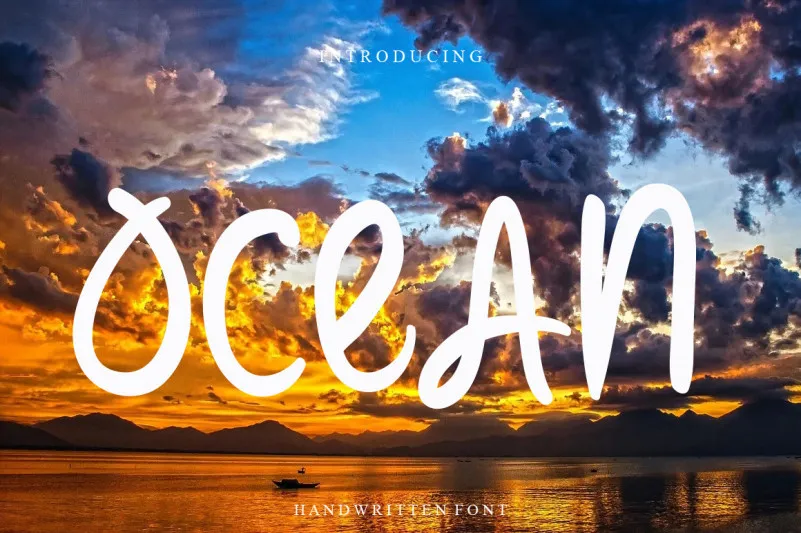
A Ocean Font é uma elegante escolha para quem busca criar designs modernos e descontraídos que transmitem alegria e frescor. Essa fonte script traz a sensação de um convite festivo, mas não se limita a isso. Seja para um baile infantil, uma festa adulta ou até mesmo um anúncio de casamento inovador, essa fonte é perfeita para dar ao seu projeto aquele toque jovial e divertido que tanto valorizamos em nossos dias. Seu designer, LevinCreative, entende a importância da personalidade de cada design e criou uma fonte fluente e amigável que se adaptará facilmente às mais variadas necessidades gráficas. Em um mundo onde tudo demanda ser mais inovador, esta font oferece um toque nostálgico e divertido que cativa instantaneamente seu público-alvo jovem e vibrante. Experimente a Ocean Font em sua próxima criação e veja como ela pode trazer vida e energia para qualquer design de texto.